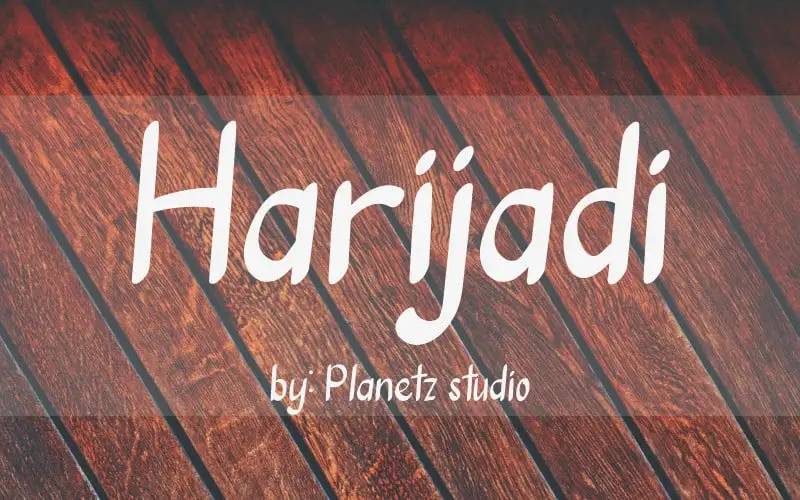
Harijadi Brush Font – Download Grátis
A Harijadi Brush Font é uma fonte autêntica criada a partir de traços feitos com um pincel. Sua fórmula leva as características naturais do estilo manuscrito, oferecendo um grau de relaxamento que a torna ideal para várias aplicações de design. Suas linhas elegantes e sua leveza permitem que ela se adapte a uma variedade de projetos, desde logomarcas até a decoração DIY em estilo criativo. Esta fonte é perfeita para personalizar seus projetos digitais, como postagens nas redes sociais ou artefatos do dia-a-dia. Com seu design natural e fluido, Harijadi Brush Font oferece um toque autêntico que se adapta a qualquer tipo de projeto visual. É uma escolha perfeita para quem valoriza um estilo único e elegante em seus projetos gráficos.